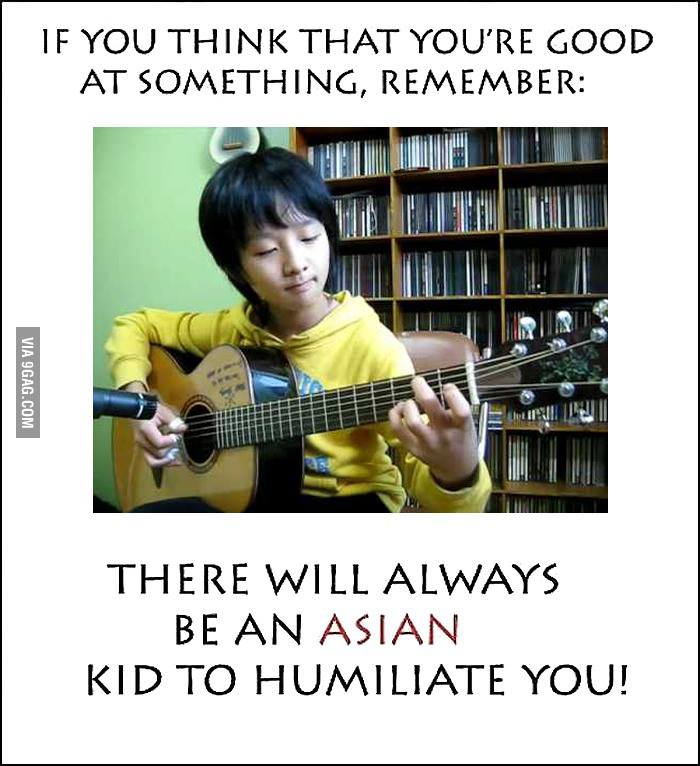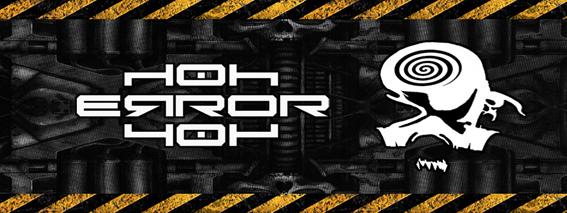
Suche bestimmte Schriftart - wie herausfinden?
Suche die Schriftart des angehängten Bildes.
Wie kann ich die rausfinden ?
Bis jetzt noch nicht fündig geworden.
Gefunden hab ichs bei google.de
Bildersuche: Castle
Ich suche auch eine Schriftart, wollte deswegen aber ehrlich gesagt keinen neuen Thread aufmachen. Daher poste ich meine Frage mal hier!
Ich suche folgende Schriftart:
Die heisst Frankfurter oder so ähnlich. Ich hab schon überall im Web gesucht, das einzige, was ich finde, sind kommerzielle also nicht kostenlose Downloads! :(
Sorry aber muss das Thema nochmal aufleben lassen!
Suche schon seit Stunden durch die oben angegeben Links find aber nirgends mein Font!
Weiß aber das es freeware war ... hatte ihn damals selber benutzt bei Bilder-erstellungen ...
ich finde diesen schrift art nicht kann mir das vieleicht jemand hier posten bitte
oder vieleicht macht sich wer die arbeit und schreibt das hier rein das ich es rauskopieren kann
ERROR 404 nur in der schrift wie es in dem foto ist bitte
Ich suche diese schriftart..
Bei diesem Logo handelt es sich mit großer Wahrscheinlichkeit um eine kundenspezifische Schrift; die speziell ineinander gelegten Buchstaben deuten stark darauf hin.